最新全球研究報告《字體、情感與短影片:世代對字體的態度》顯示,全球年輕世代將字體選擇視為線上身份、自我表達與社交參與的核心。
美國麻薩諸塞州沃本鎮,2025年10月6日 — 全球字體與科技領導品牌蒙納(Monotype Imaging Inc.)今日發布其最新跨國報告《字體、情感與短影片:世代對字體的態度》的研究發現,該報告為公司持續進行的年度字體報告「Re:Vision」計畫的一部分。
這項由Monotype委託、獨立研究公司Censuswide執行的研究,調查了來自美國、英國、西班牙、德國、法國及巴西超過12,000名16至79歲的社交媒體用戶,揭示了各世代在社交媒體上對字體的感知與使用存在顯著差異——其中Z世代與千禧世代最懂得字體選擇所蘊含的力量。
研究顯示,各世代普遍認同字體的價值,近70%的社交媒體用戶認為字體選擇對於發文十分重要。這種看法在年輕的數位原生世代中更為強烈:79%的Z世代與78%的千禧世代同意字體是發文的關鍵要素。
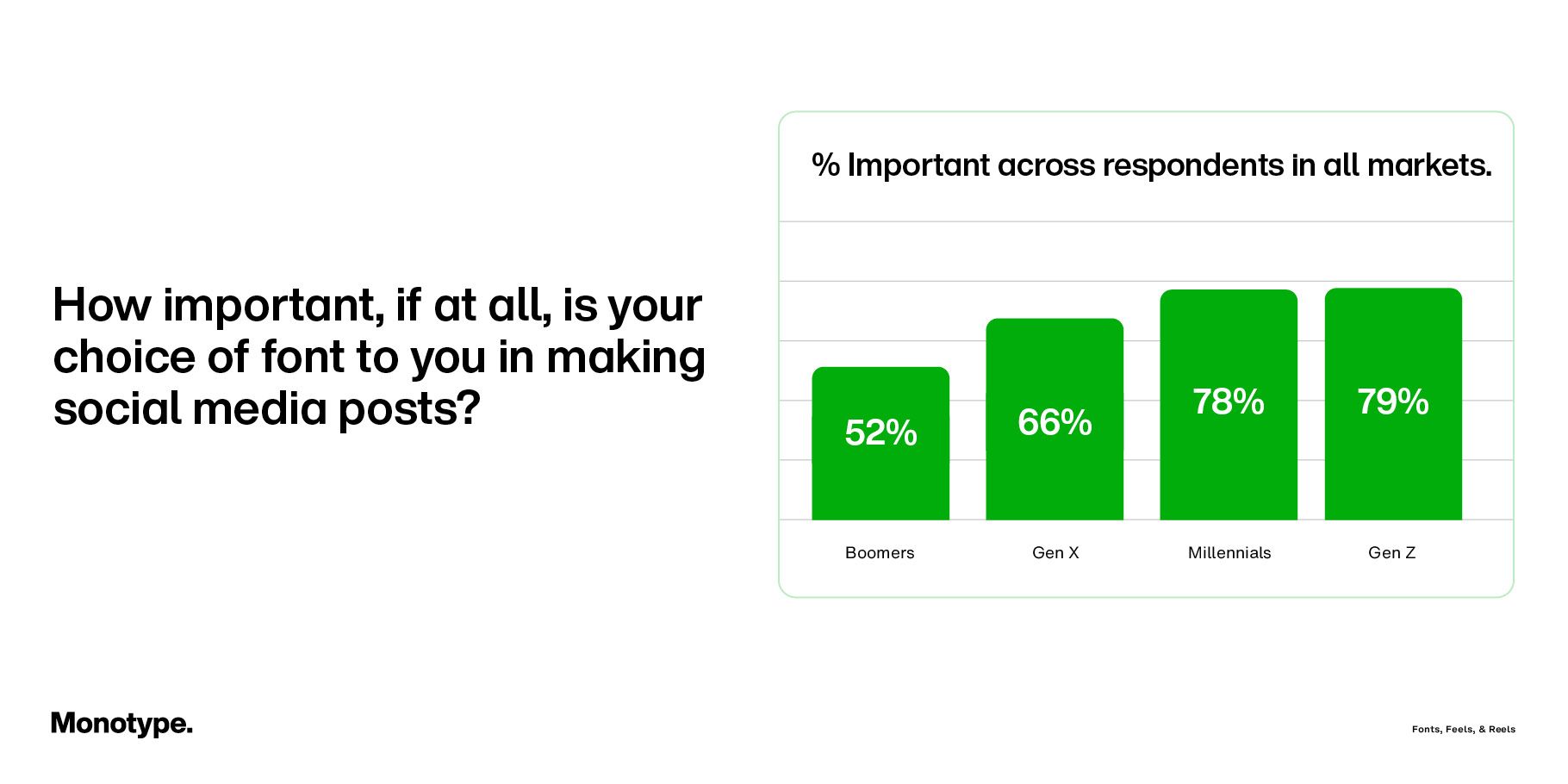
根據研究結果,從Z世代到嬰兒潮世代可以歸納出以下四大發現:
除了演算法外,字體選擇提升參與度
78%的受訪者認同使用獨特精選字體能有效提升貼文按讚、分享與評論數。Z世代與千禧世代認同度更高達87%與86%,相當於每10人中就有超過8人肯定字體的影響力。字體選擇不足,年輕世代最困擾
超過半數的Z世代(55%)與千禧世代(52)坦言對常用社交平台的字體選擇受限感到不滿,這顯示社交媒體平台在協助用戶自我表達方面仍有強化空間。創作者跨出平台,追尋字體自由
在使用外部設計工具製作貼文的創作者中,高達71%明確表示是為了獲得更多字體選擇與控制權,這股風潮正由數位原生世代Z世代與千禧世代引領。字體讓文字擁有表情溫度
對65%的Z世代與67%的千禧世代而言,字體已成為自我表達的核心要素,能直接展現個人特色、真實性與風格品味。
Monotype執行創意總監Tom Foley對此現象精準詮釋:「當今字體對個人表達的重要性,早已堪比衣著打扮、音樂品味與影音創作。我們的研究顯示,對從未經歷過前社交媒體時代的Z世代而言,字體選擇早已超越單純設計考量——它們是形塑網路連結、溝通模式與創作風格的強力身份宣言。」
這項發現證實:全球不同年齡層的使用者都在乎字體選擇。字體從來不是靜止的存在,而是會呼吸的設計媒介——它既能承載個人特色,又能塑造視覺感受,更在無形間主導著數位互動的節奏。而年輕世代對此有著超乎常人的敏銳度,他們不僅精通如何運用字體強化表達,更懂得解讀他人字體背後的潛台詞。
對於消費者、品牌方、創作者、網紅乃至各大數位平台而言,這無疑是個明確的訊號:字體,就是你的沉默代言人。當平台能提供豐富多元的字體選擇,就等於為Z世代與千禧世代搭建了盡情展現自我的舞台——這不僅是搶佔當代用戶心智的關鍵策略,更是為未來全世代、全渠道的長期認同鋪路。